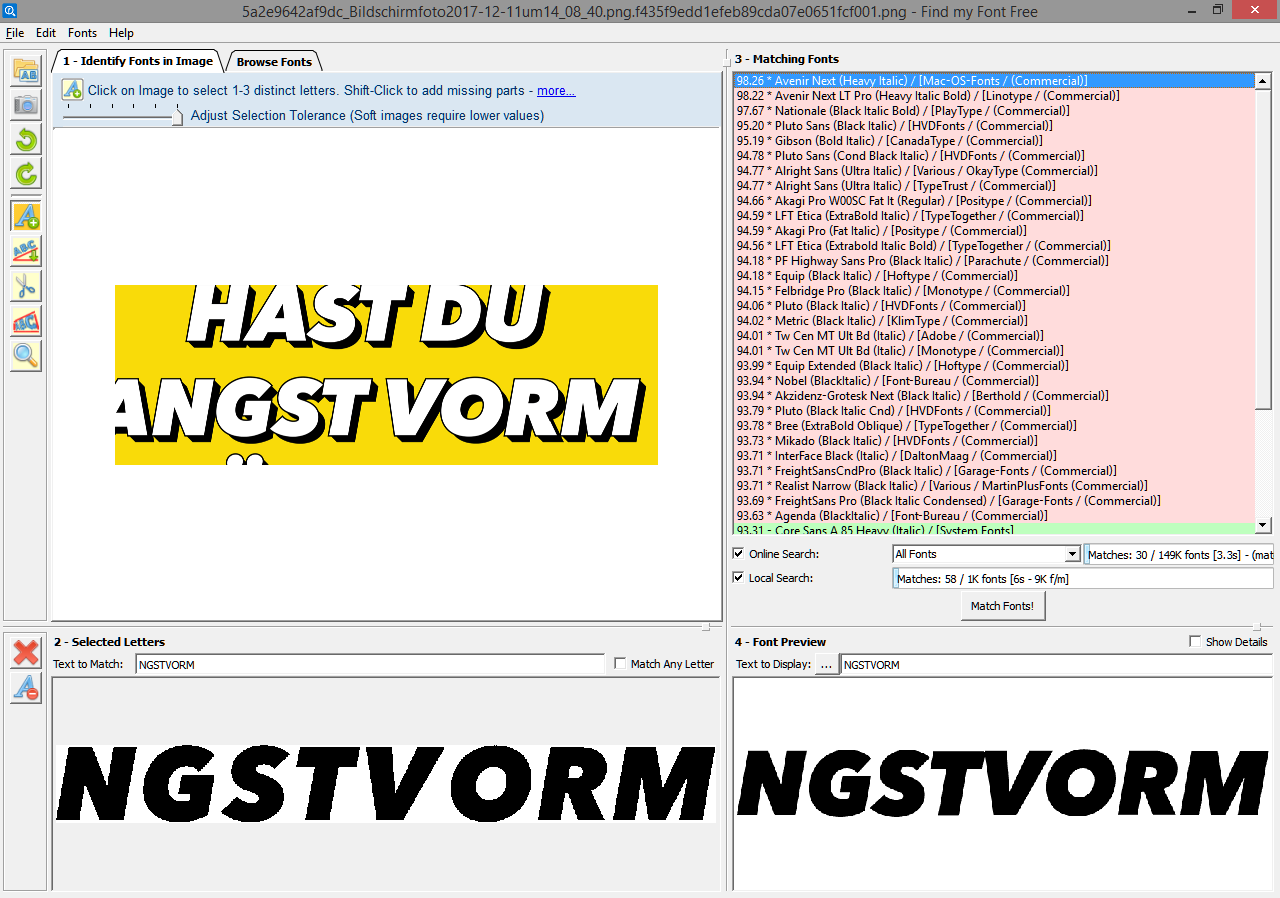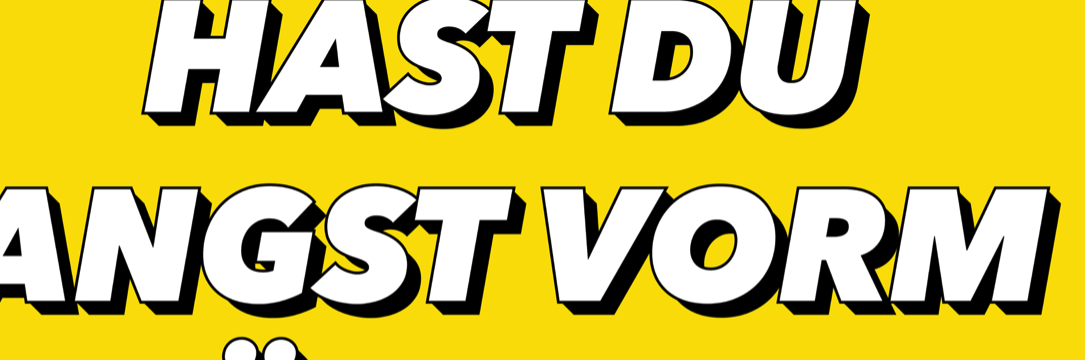
Welche Schrift ist das? (Schatten)
kann mir jemand weiterhelfen, was das für eine Schrift ist?
Zum Font:
Der Schatten bzw. die outline ist manuel erstellt wurden.
Ähnlich:
Futura Pro ExtraBold Oblique
Gibson Bold Italic
Das ist die Avenir Next Pro Heavy Italic.